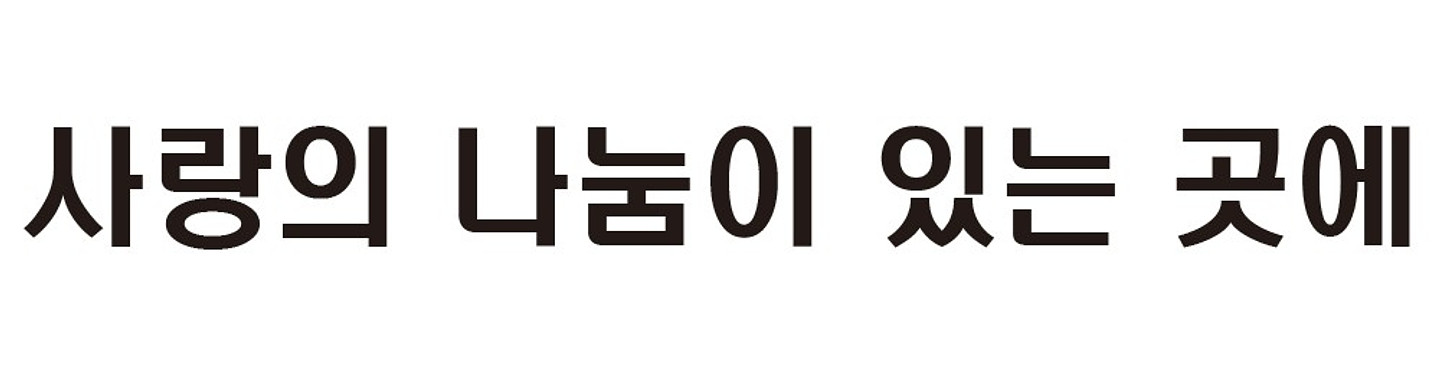
예배 찬양 PPT에 자주 쓰이는 폰트입니다. 인공지능에게 폰트를 물어봤고 결론은 사진에서 하얀 테두리와 그림자 효과를 제외하고 확인했을 때 굵은 고딕 계열의 폰트라고 추정했고 나눔스퀘어 ExtraBold / Noto Sans KR Black를 후보로 뒀으나, 둘 다 PPT에서 기존 폰트가 쓰인 사진과 불일치하였습니다. 폰트가 무엇인지 알면 기존 찬양 ppt에 내용을 추가할 수 있어서 조사해주시면 감사하겠습니다.
HY헤드라인
HY헤드라인 인 것 같네요. 굵기가 M인지 B인지는 모르겠지만 제가 올린 사진이 M인데 여기에 획을 0.25정도만 줘도 올리신 사진이랑 거의 동일하게 보입니다. 컴퓨터에 기본적으로 설치되어 있을 수도 있습니다.